水波效果的文字用ps怎么做?
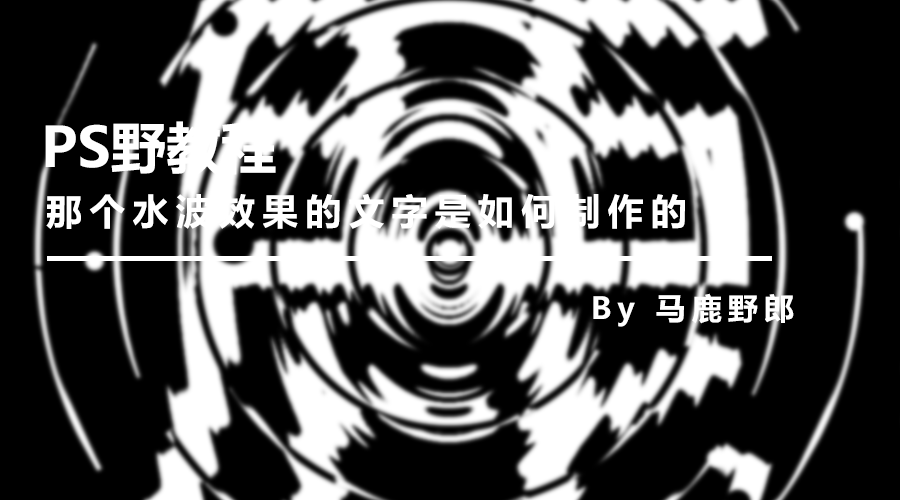
这种类似水波效果的文字我的感觉是用PS滤镜做出来的,老实说其实我很怕研究滤镜做出来的效果,因为尝试的过程比较长,但是一旦尝试出来了写不了多少内容。
还在运气比较好,这个效果没试多久,感觉效果就差不多了。
来吧,今天我们就来看看这个水波效果的文字是如何制作的吧!
开始之前啰嗦一句,基础的文字以及图形我还是习惯用Ai来弄会比较方便,当然你用PS也是可以的,看习惯吧!
首先打开Ai,如图所示选择一个合适的字体,调整其大小,颜色可以先就用黑色的,后面我们再改变都可以:
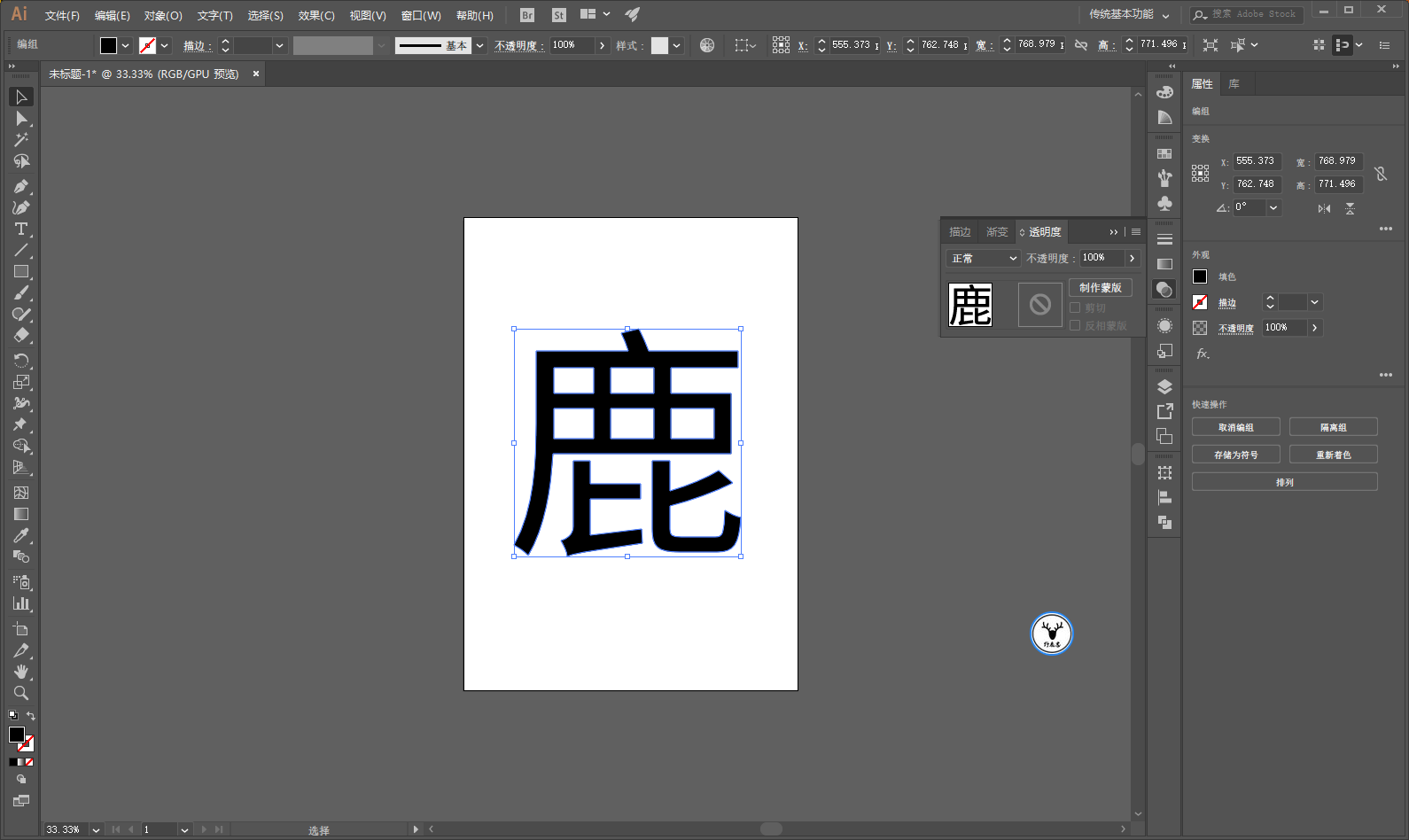
如图所示画一个描边圆,大小刚好包住文字就可以了,描边的粗细看着效果来就好:
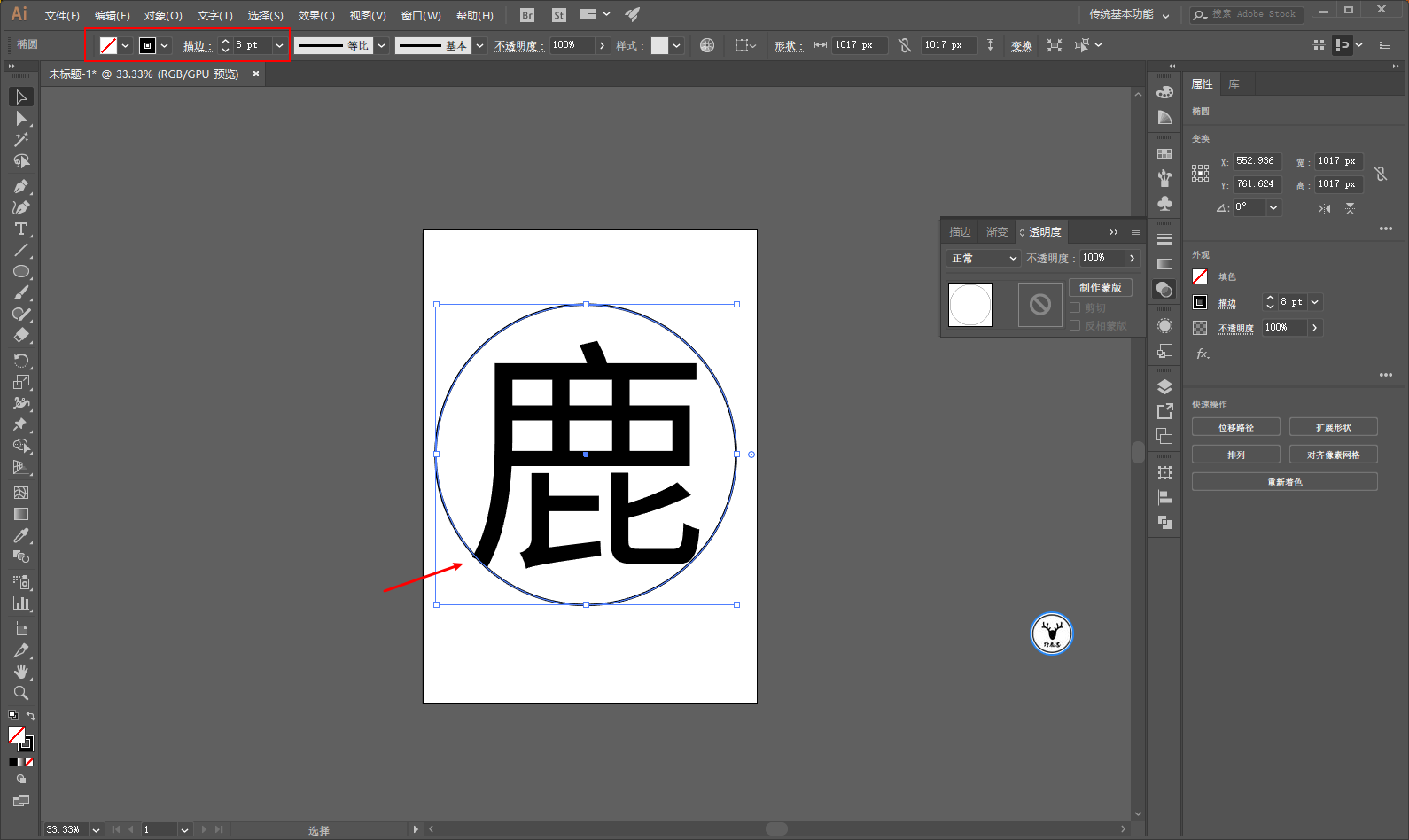
选中描边圆,鼠标右键执行变换-缩放,选择等比缩放,缩放的比例大家也看着效果来就好,注意不要缩放描边和效果,然后点击复制:
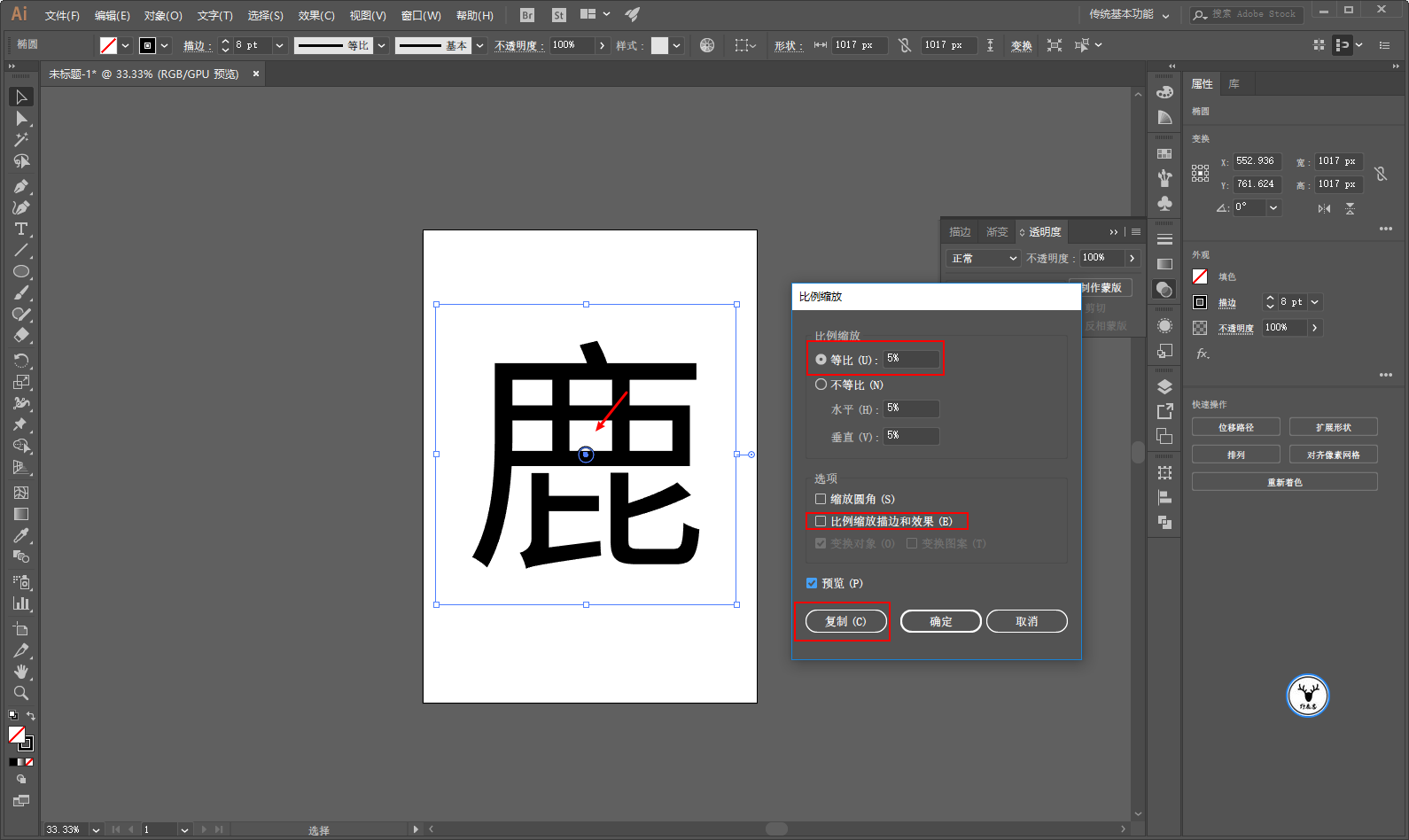
在对两个圆进行混合,混合的步数我觉得4就可以了:
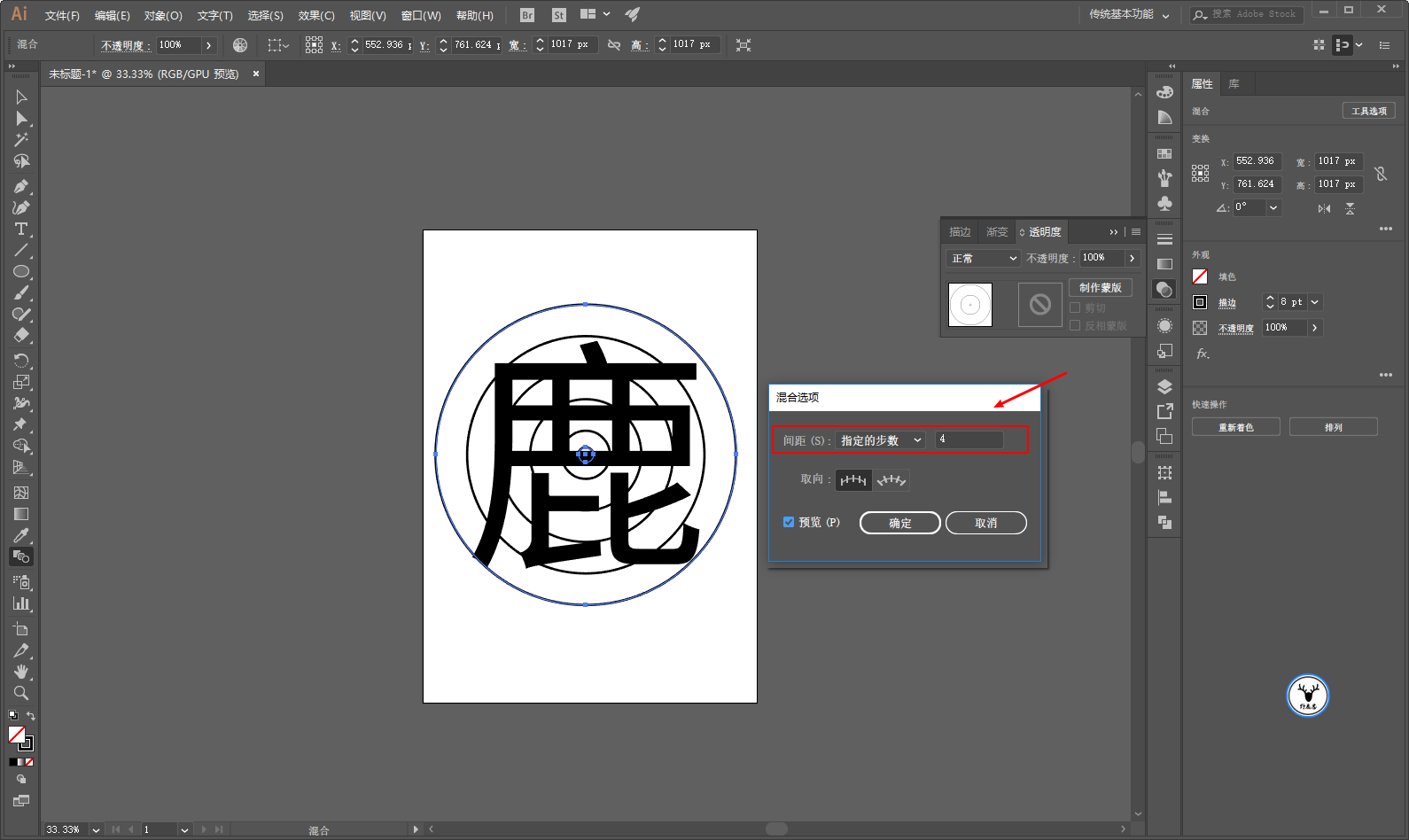
当然你也可以如原图所示画一些圆圈或者圆点出来做装饰,过程中为了方便观察可以暂时降低一点文字的不透明度,记得编好组哦:
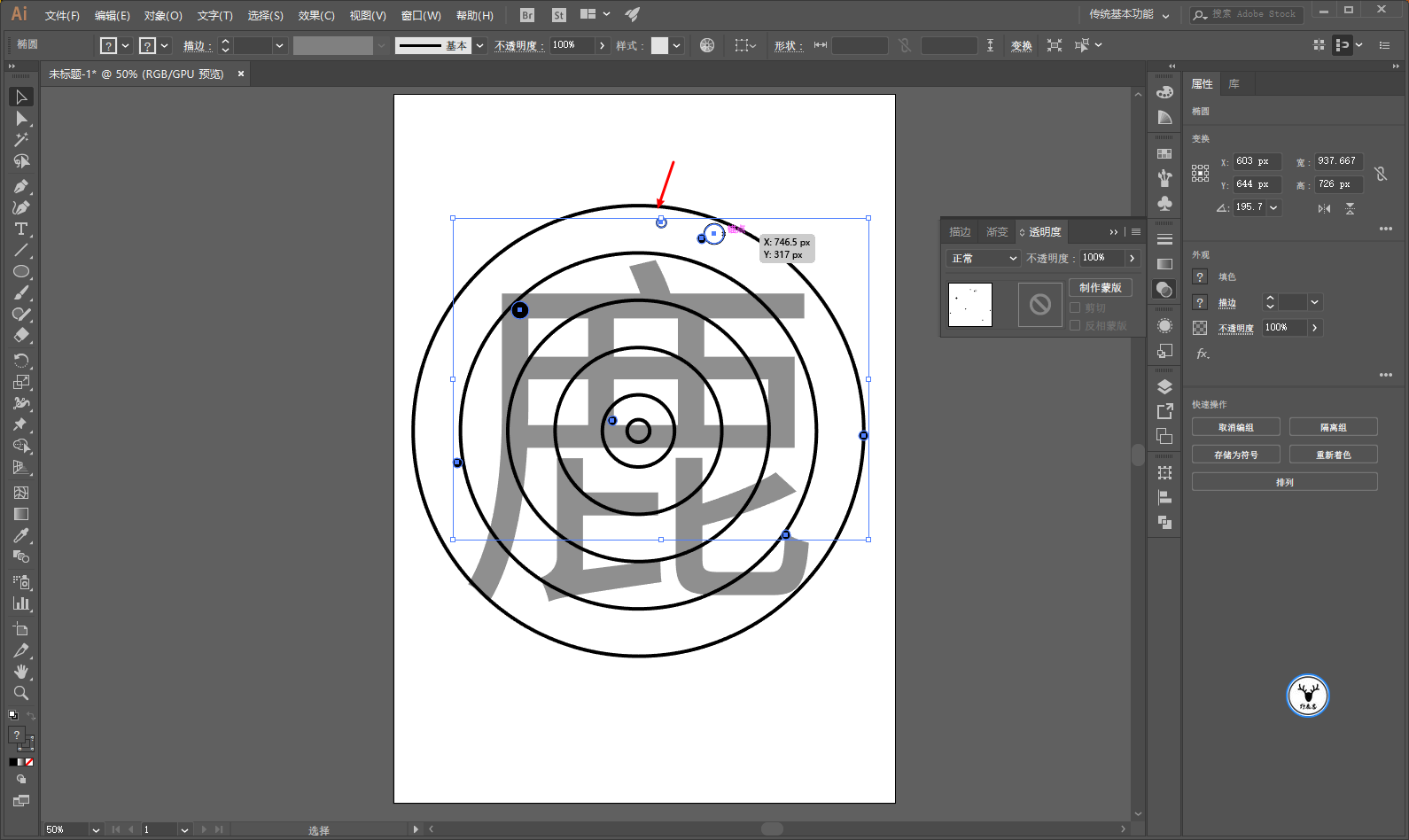
至此差不多就可以到PS里去处理了,把三个部分分别拖进PS里:
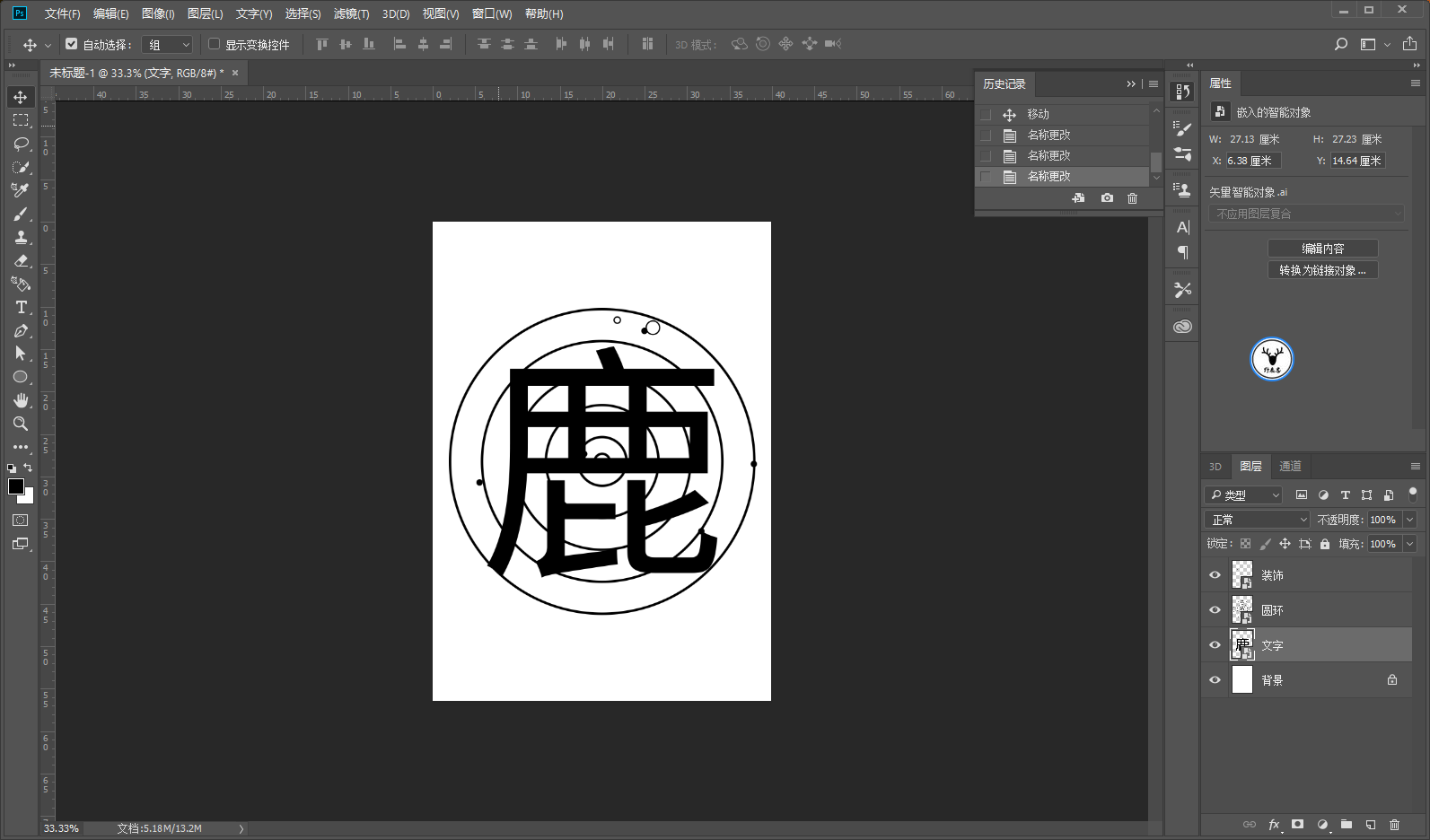
按住ctrl键鼠标单击圆环图层缩略图载入选区,然后ctrl+shift+i选择选区的反相以后。
给文字图层添加图层蒙版,隐藏掉圆环图层,可以得到如图所示的效果:
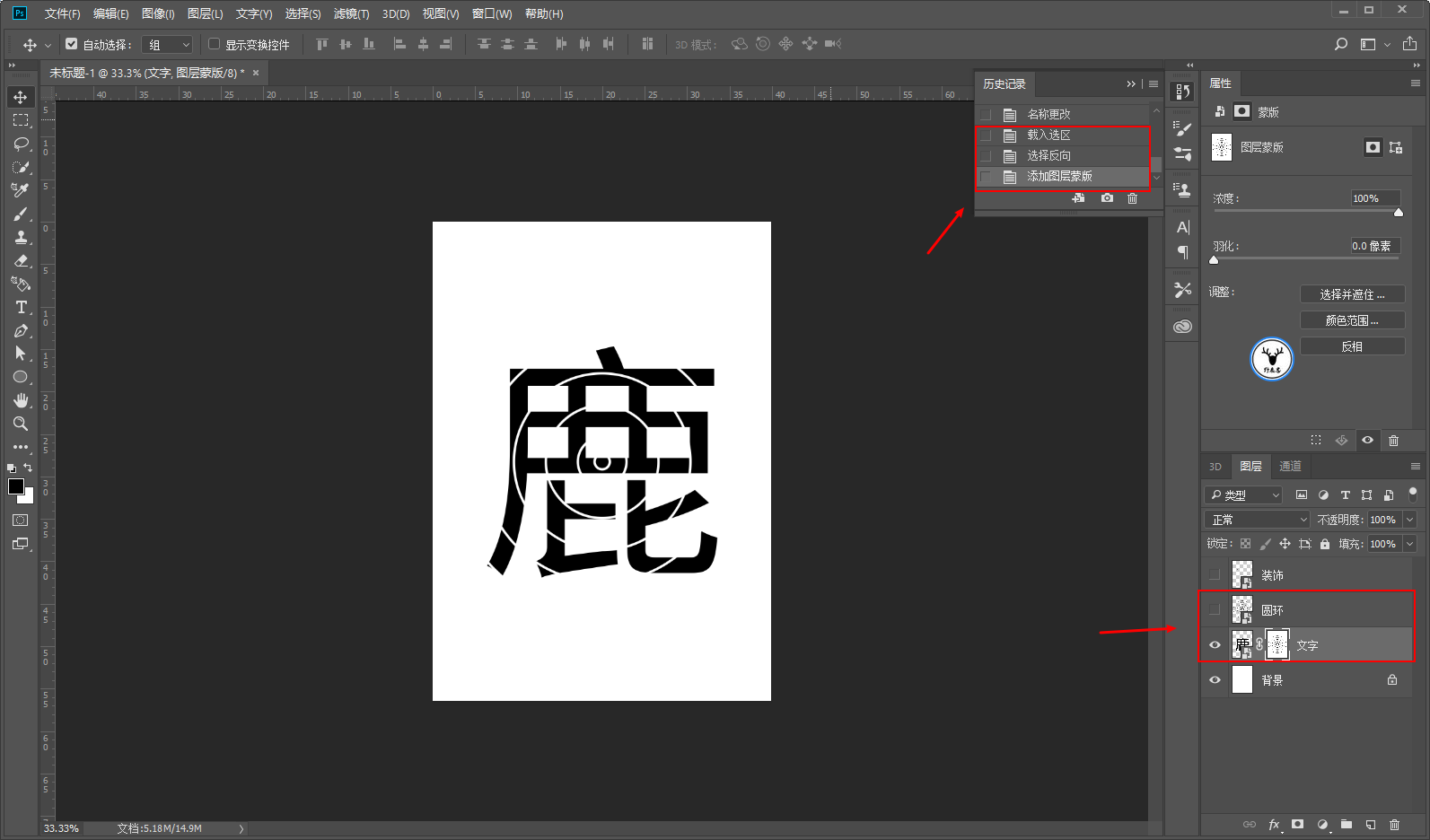
给文字图层添加滤镜-扭曲-水波:
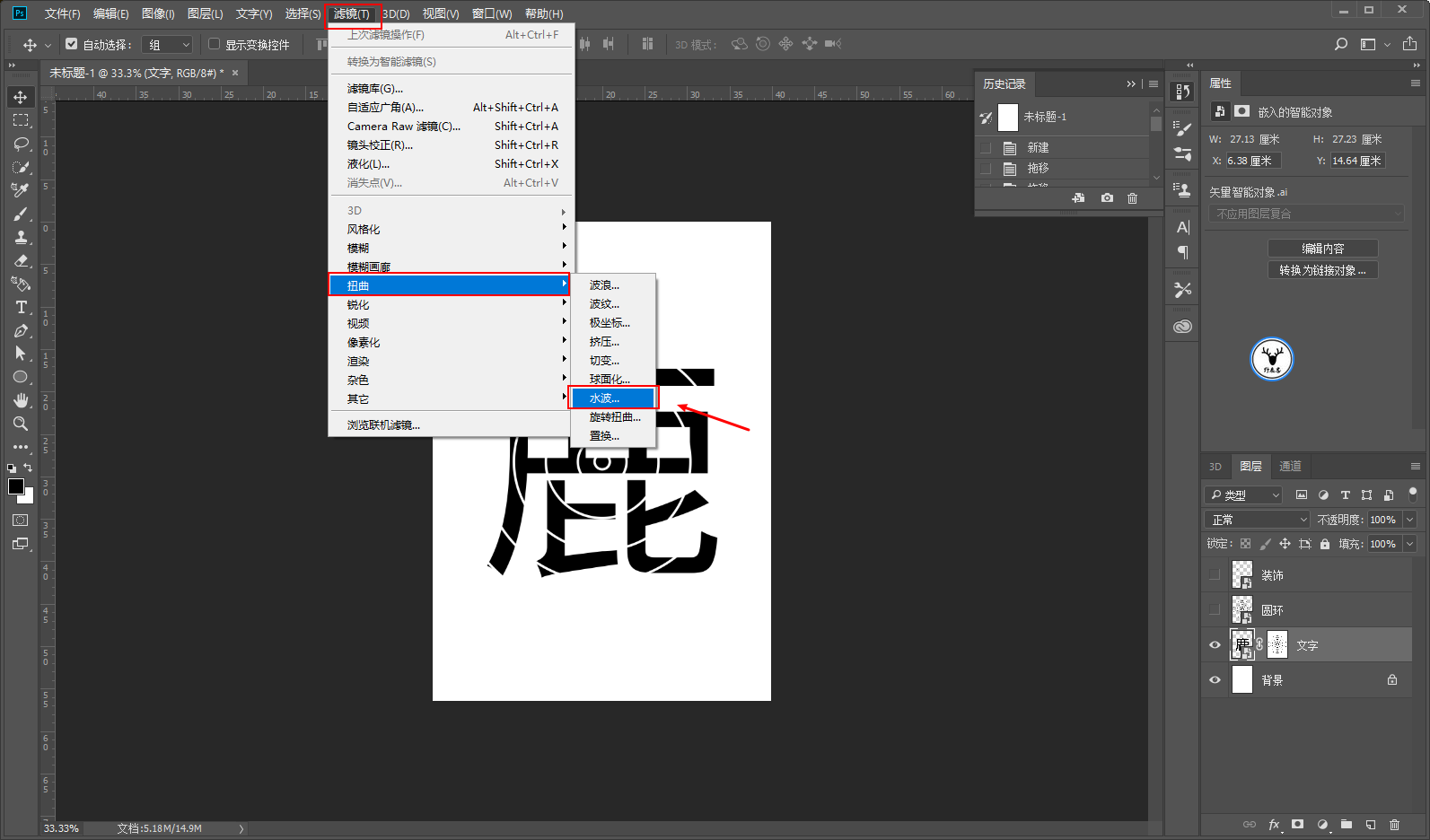
样式选择中心向外,样式以及数量的参数我这里给到了最大:
如果觉得效果不够强烈,可以再执行一次水波滤镜:
显示出圆环图层,按住ctrl鼠标单击圆环缩略图载入原图图层的选区,然后按住ctrl+shift鼠标点击文字图层的缩略图。
得到两个选区的差集以后,给圆环图层添加图层蒙版,得到如图所示的效果:
可以再用黑色的实边画笔,在圆环的图层蒙版上随机的擦掉一些:
同样可以给圆环图层也添加一个水波滤镜:
这个时候就可以给背景添加一个黑色的纯色填充图层,并且通过图层颜色叠加将文字等颜色变成白色:
你还可以再新建一个空白图层,用黑色实边的画笔在文字上适当的点一下进行修饰:
仔细观察觉得原图正中间有一个圆钮,所以我这里又在中间画了一个椭圆,添加了斜面与浮雕的图层样式:
最后码字排版导样机,老三样看看效果吧: